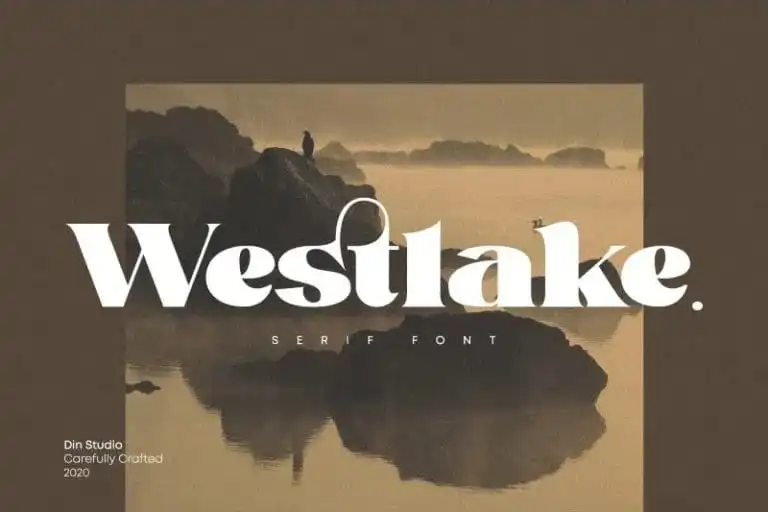
A fonte Westlake Serif é uma escolha intrigante para quem busca sofisticação em cada letra. Seu design elegante e delicado tem a peculiaridade de desafiar os olhos com suas curvas levemente arredondadas, mas mante-se fiel à sua classe. Foi criada pelo designer Din Studio na 99designs. Este font se destaca como uma escolha ideal para projetos profissionais de branding. Seja para criar um logo memorável, reforçar a identidade visual ou traduzir frases com impacto, Westlake Serif é uma excelente opção. Sua beleza e elegância fazem do seu uso em tudo, desde cartazes até o design de websites, um passeio estético. Estamos ansiosos para que você descubra os inúmeros detalhes únicos e belos que cada letra da fonte Westlake Serif oferece. Seja em uma página de blog ou em qualquer projeto visual profissional, esta font vai dar um toque refinado a qualquer trabalho de design.